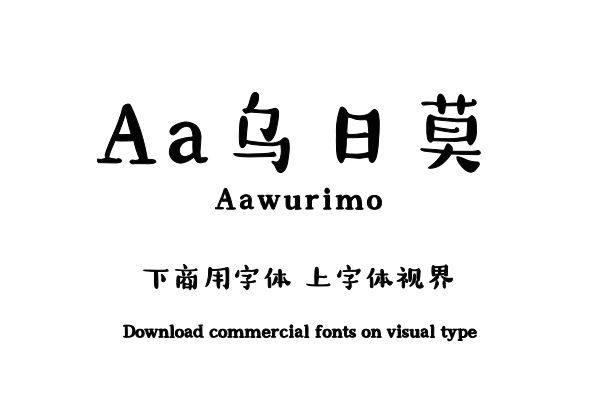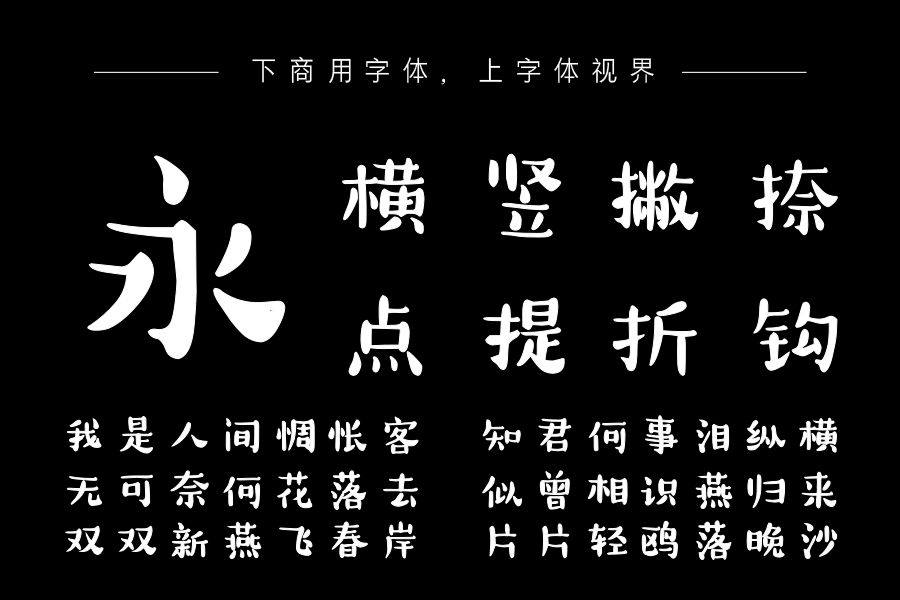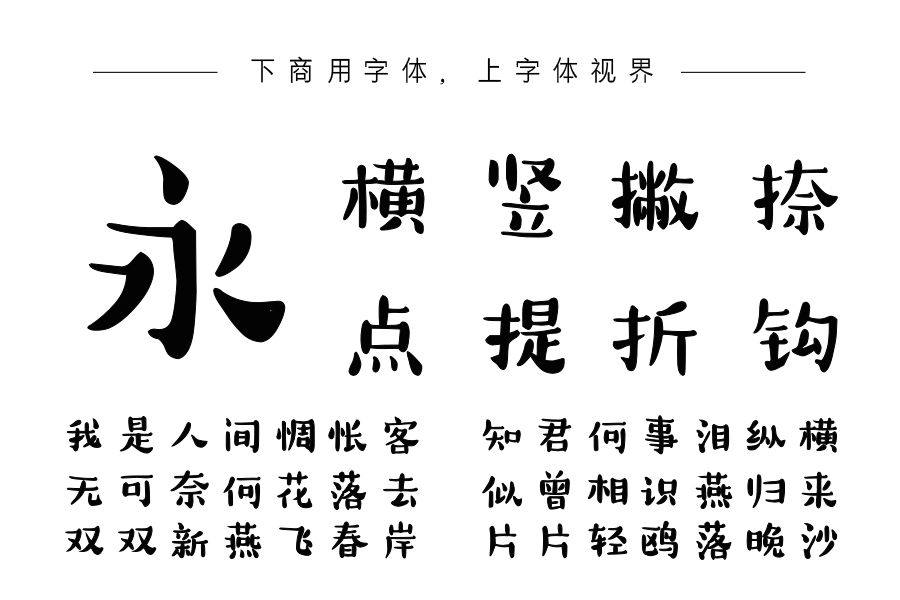
Aa乌日莫,是一款涂鸦风格的手写体,字形略方、大小错落有节奏,笔画粗细对比明显、有涂鸦衬角装饰。字体风格生动、呆萌,个性独特。多做为标题使用,适用场景广泛。购买须知:“下载服务费”与“字体VIP”所获得字体 仅用于个人非商用, 商用请联系付费授权。本字体为电脑用字,手机没有root权限不支持直接手机换字(手机如何root,请自行百度搜索教程)。购买前请先 了解清楚后再付款 ,字体为虚拟产品无法回收 一旦购买不支持退款。